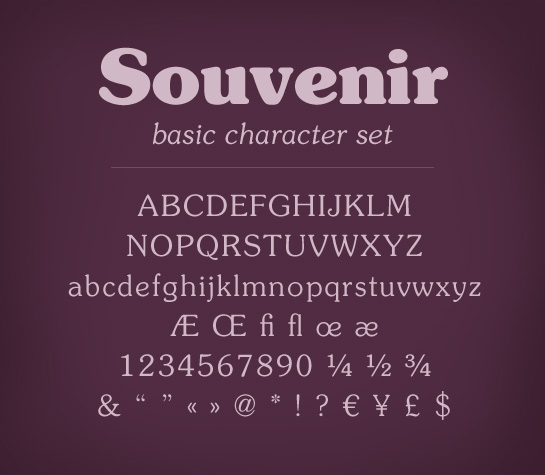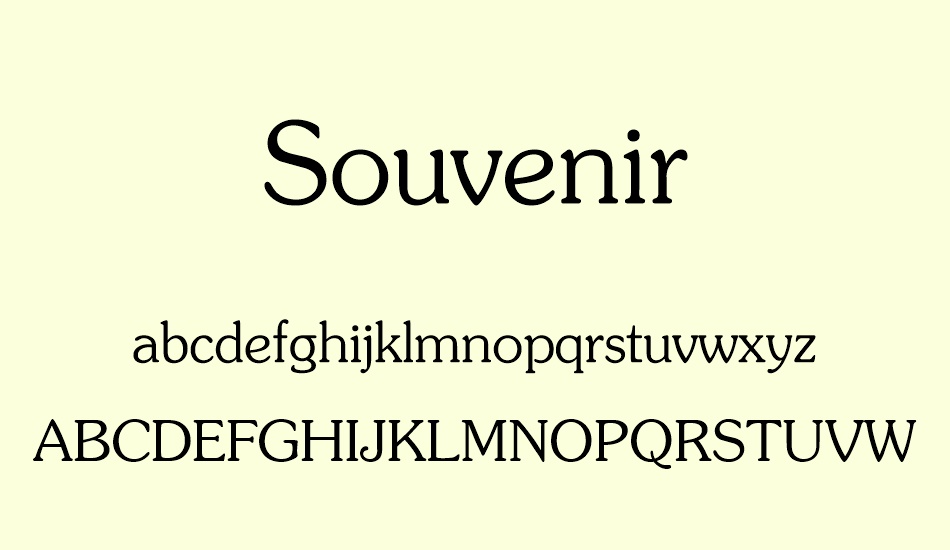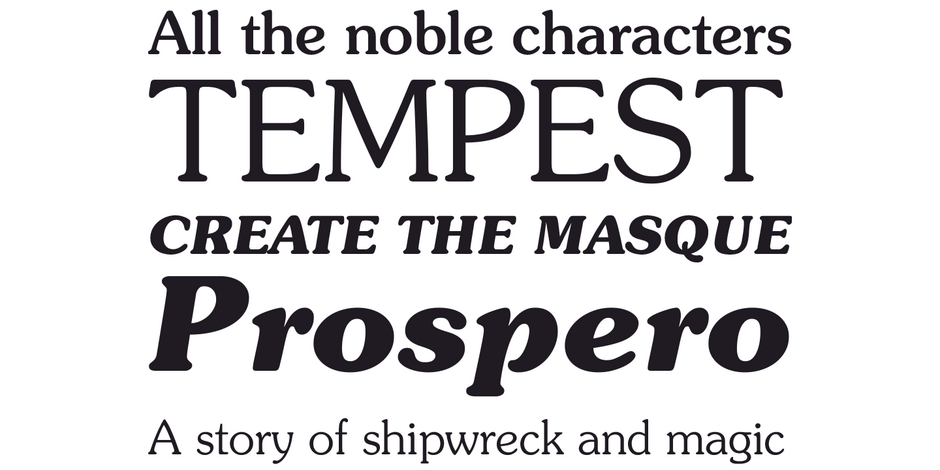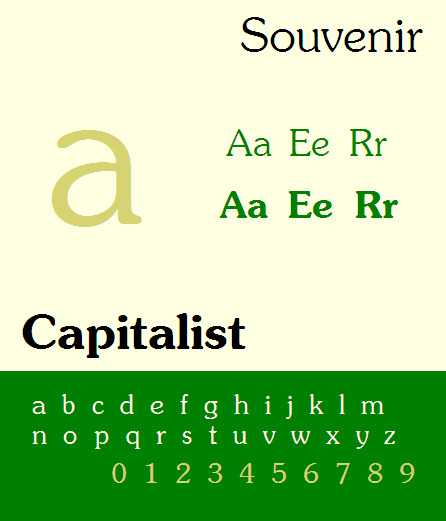
Font Souvenir là bộ phông chữ có chân (Serif) kinh điển mang phong cách ấm áp, mềm mại và tràn đầy cảm xúc hoài niệm, được sáng tạo ban đầu bởi Morris Fuller Benton vào năm 1914 và sau đó được huyền thoại Ed Benguiat hoàn thiện cho xưởng đúc chữ ITC vào thập niên 1970. Với các đầu chân chữ được bo tròn duyên dáng cùng cấu trúc đường cong thoải mái, Souvenir là lựa chọn hoàn mỹ cho các thiết kế bao bì thực phẩm hữu cơ, tiệm bánh thủ công, mỹ phẩm thiên nhiên và các ấn phẩm phong cách Vintage gần gũi. Doozypack.vn cung cấp link tải font Souvenir Việt hóa chuẩn kỹ thuật, giúp bạn sở hữu phông chữ độc đáo này mà không lo gặp bất kỳ lỗi hiển thị dấu thanh nào khi thiết kế in ấn.
Đặc điểm thẩm mỹ độc đáo của bộ font Souvenir
Souvenir không đi theo sự sắc nhọn hay nghiêm nghị của các dòng phông chữ có chân truyền thống; nó mở ra một không gian thị giác thân thiện, nhẹ nhàng và ngập tràn sự thư thái.
Đường nét uốn cong mềm mại và chân chữ bo tròn ấm áp
Đặc trưng lớn nhất của Font Souvenir là các nét chân chữ (serif) không bị cắt phẳng hay vát nhọn mà được bo tròn một cách tinh tế. Cấu trúc chữ sở hữu những đường cong nở rộng, trục chữ hơi nghiêng tự nhiên tạo cảm giác như những con chữ đang mỉm cười chào đón người xem. Phong cách này mang lại sự mộc mạc, lành tính và an tâm, cực kỳ phù hợp với các thương hiệu hướng đến giá trị gia đình, sức khỏe và sản phẩm xanh.
Phong cách Vintage thập niên 70 gần gũi và giàu cảm xúc
Souvenir gắn liền với thời kỳ hoàng kim của văn hóa Retro thập niên 1970, nơi sự tự do và tính nhân văn được đề cao. Khi đặt font Souvenir Việt hóa làm tiêu đề trên bao bì, thương hiệu của bạn sẽ ngay lập tức toát lên vẻ lâu đời, chân thành và đáng tin cậy, giúp khách hàng cảm nhận được sự tỉ mỉ của người làm nghề thủ công truyền thống.
Ưu điểm nổi bật của bản font Souvenir Việt hóa
Khi ứng dụng các phông chữ mang tính hoài cổ vào thị trường trong nước, sự chỉn chu về dấu câu là yếu tố quyết định đến tính chuyên nghiệp của bản thiết kế:
- Khắc phục triệt để lỗi dấu tiếng Việt: Phiên bản Việt hóa của Souvenir đã được đội ngũ thiết kế trau chuốt thủ công từng dấu câu. Các dấu sắc, huyền, hỏi, ngã, nặng được vẽ với các góc bo mềm mại đồng điệu cùng thân chữ gốc, không gây cảm giác chắp vá hay đè nét làm mất tính thẩm mỹ.
- Bao bì thực phẩm hữu cơ & Nông sản sấy: Nét chữ bo tròn kết hợp hoàn hảo cùng chất liệu giấy Kraft nâu thô mộc, tạo nên phong cách Vintage nguyên bản, sạch sẽ và an toàn.
- Hộp bánh ngọt thủ công (Bakery & Pastry): Tiêu đề thương hiệu in bằng font Souvenir trên hộp giấy Ivory mang lại cảm giác ngọt ngào, thơm ngon và đậm đà phong vị gia đình.
- Tem nhãn mỹ phẩm thiên nhiên & Xà phòng handmade: Cấu trúc chữ thanh thoát giúp nhãn dán chai lọ toát lên vẻ lành tính, mộc mạc và thân thiện với người dùng.
03 Lưu ý kỹ thuật khi in ấn với phông chữ chân tròn Souvenir
- Kiểm soát hiện tượng tràn mực (Dot Gain) tại khe chân chữ: Do phần chân chữ của Souvenir có độ dày vừa phải, các khe nối chân chữ có thể bị mực lấp đầy nếu in trên giấy hút mực nhanh như giấy Kraft. Designer nên tăng nhẹ khoảng cách chữ (Tracking) để bản in thông thoáng.
- Gia công ép kim mờ (Matte Gold): Nhờ cấu trúc nét chữ mềm mại, Souvenir cực kỳ phù hợp cho kỹ thuật ép kim nhũ vàng cát hoặc nhũ đồng trên nền hộp tối màu, tạo vẻ sang trọng nhưng vẫn ấm áp.